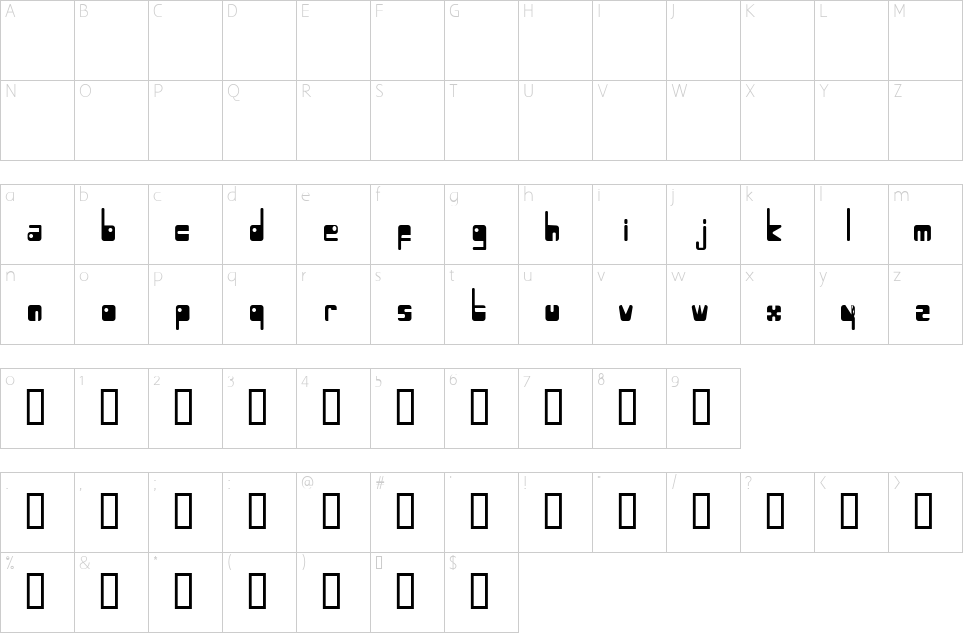
Atmosphere Font – Download Grátis
A fonte ‘Atmosphere’ é uma criação do designer Elefont, disponível para download tanto para Windows quanto para Mac. Inspirada na sensação de beleza natural e atmosfera poética, esta fonte é ideal para quem busca uma paleta de caracteres que transmita harmonia e harmonia entre o mundo digital e o mundo real. Com uma aparência limpa e suave, a ‘Atmosphere’ é perfeita para design de websites, design gráfico de e-mail e até mesmo para o design de materiais de impressão. Download a sua cópia agora e descubra como essa fonte pode transformar seu design. Através de sua natureza elegante e sua habilidade em combinar elegância com simplicidade, a ‘Atmosphere’ é uma fonte perfeita para projetos que querem expressar atmosfera e harmonia.